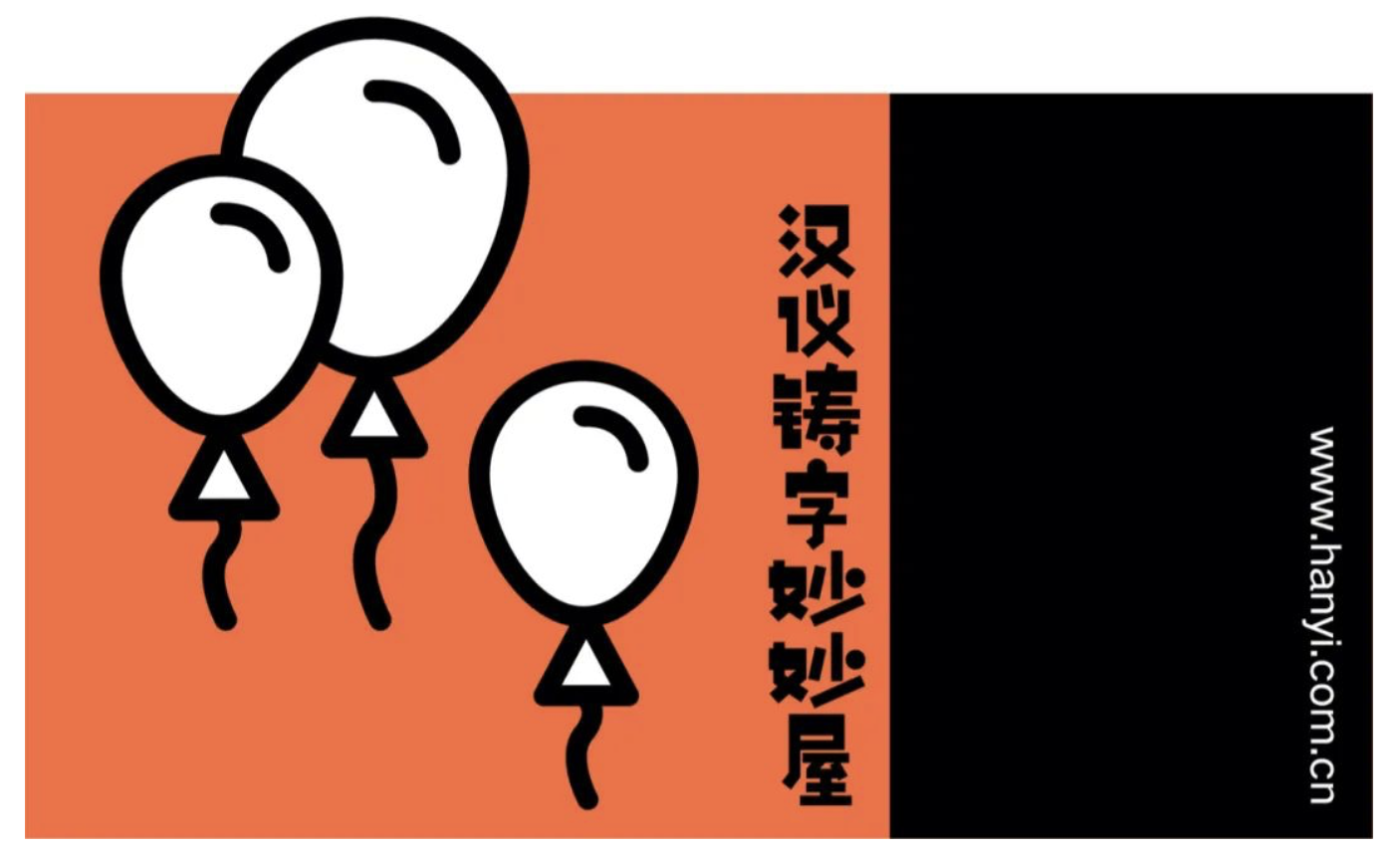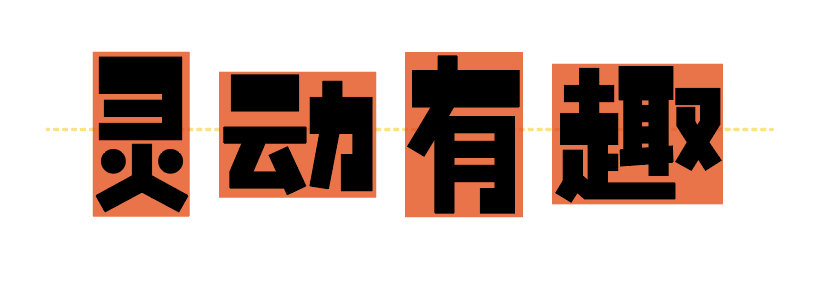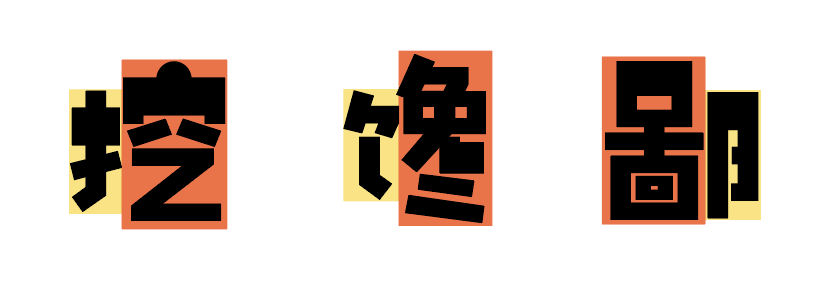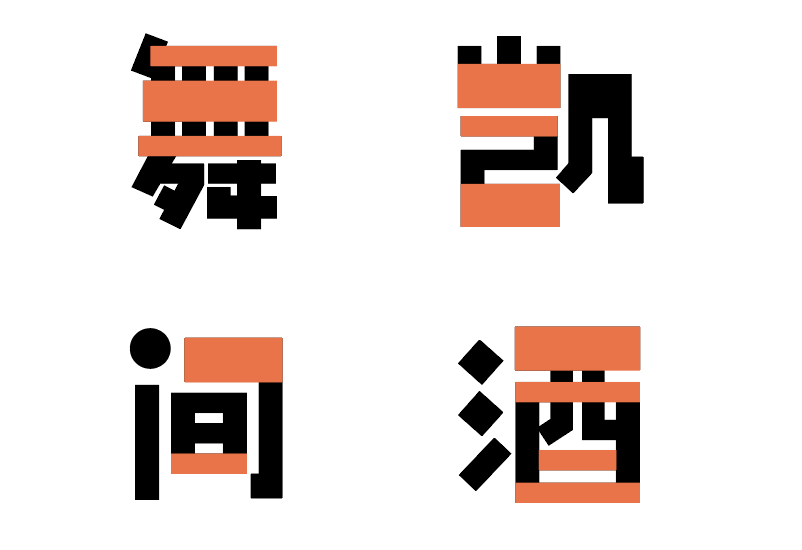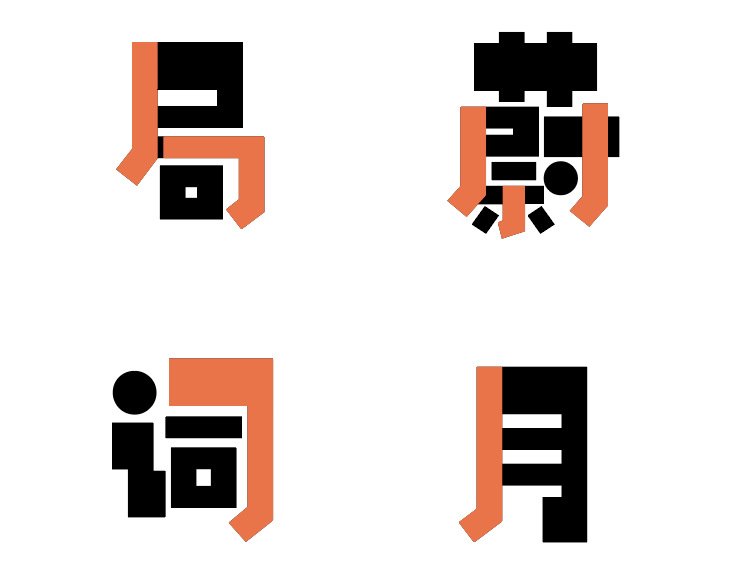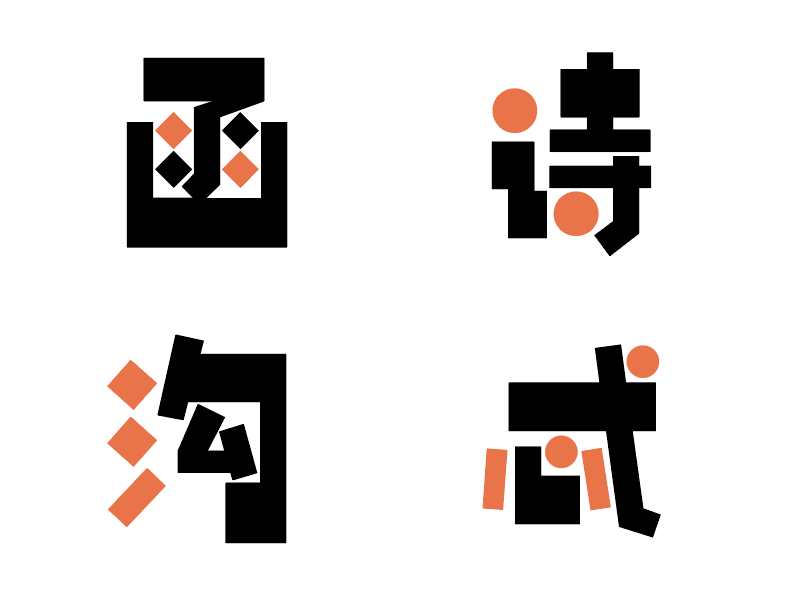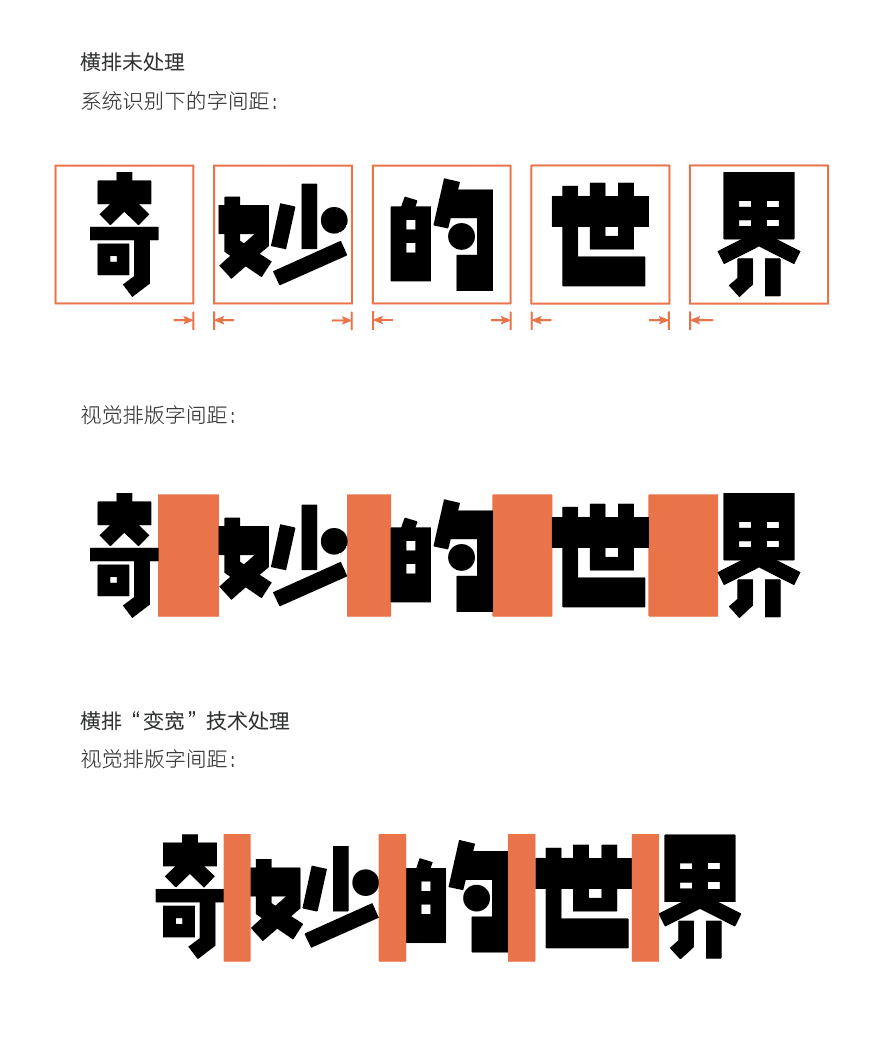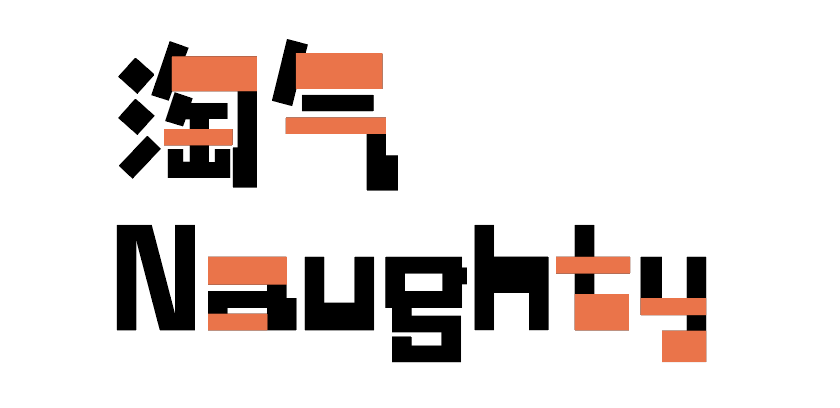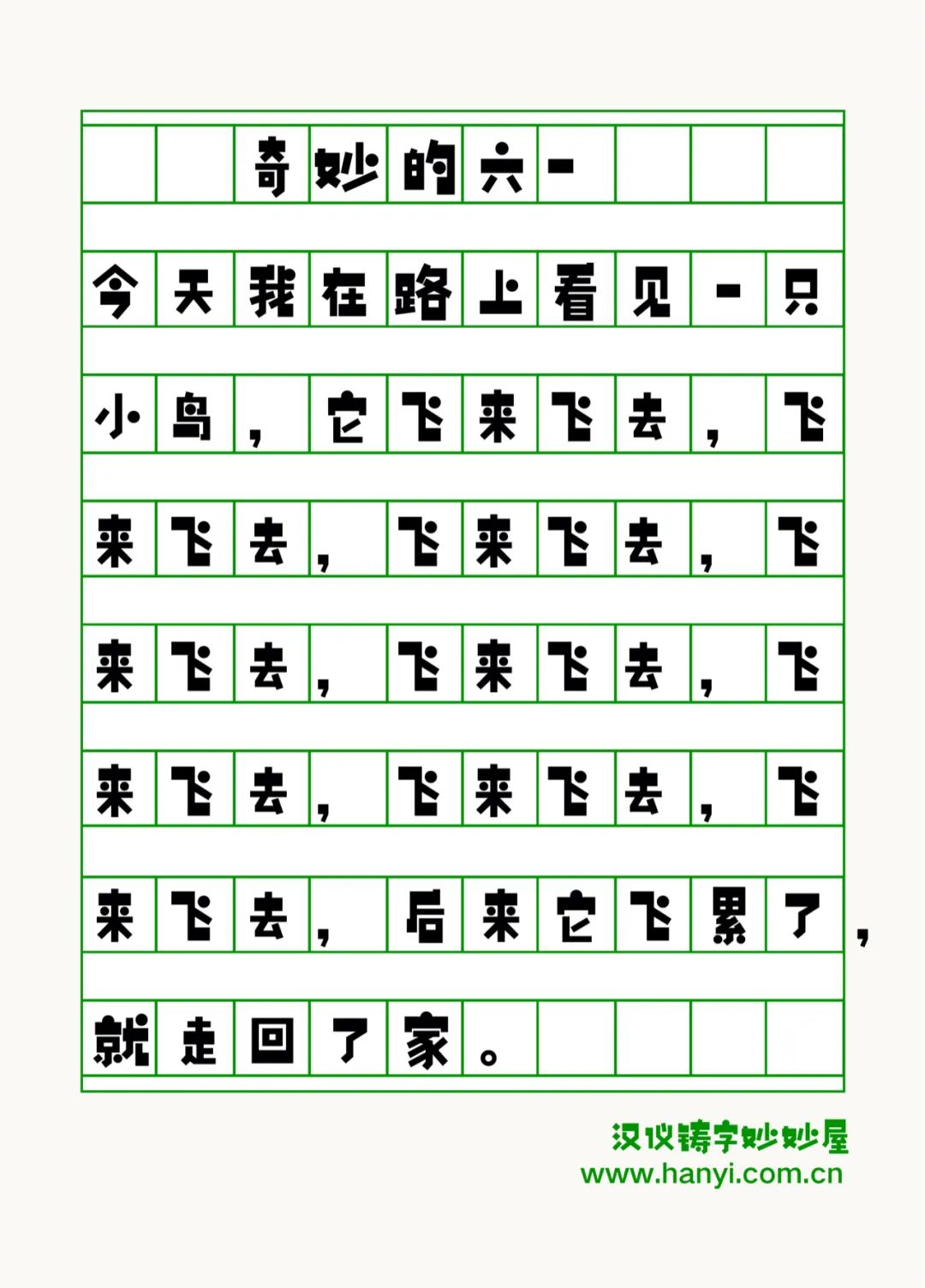
汉仪铸字妙妙屋字体介绍,汉仪铸字妙妙屋设计灵感
汉仪铸字妙妙屋 | 整体特点
“汉仪铸字妙妙屋”是汉仪旗下的“铸字社工作室”打造的一款逗趣可爱、动感活泼的创意美术标题字。它的字形变化多样,笔画粗细对比强烈,组合起来富有节奏感。
汉仪铸字妙妙屋 | 字形多变
“汉仪铸字妙妙屋”的字形多变,依据字体结构而呈现出或长或方的节奏变化,十分俏皮可爱。
汉仪铸字妙妙屋 | 结构灵活
“汉仪铸字妙妙屋”部分字体的偏旁与部首版率占比差距大,单字结构变化丰富,为字体增添了许多趣味性。
汉仪铸字妙妙屋 | 笔画活泼
“汉仪铸字妙妙屋”的横笔画粗细不一,主副笔画层次变化鲜明。在横笔画较多的字体结构当中,通过对笔画粗细及黑白空间的相对调整,使字体灰度均匀。
“汉仪铸字妙妙屋”在竖撇、竖钩和横折钩笔画的收笔处采用了折笔的处理方式,使字体更加动感活泼。
“汉仪铸字妙妙屋”点笔画的形状有圆形、矩形和菱形三种不同的设计,根据具体相关的字形而使用。
汉仪铸字妙妙屋 | 技术特点
由于“汉仪铸字妙妙屋”不同字体字面差异较大,在考虑到排版使用上的体验感后,我们在技术上采用了字间距变宽的处理方式,使字体的排版效果更加舒适自然。
汉仪铸字妙妙屋 | 中西文匹配
“汉仪铸字妙妙屋”的西文同样具有笔画粗细不一的特点,使西文更加俏皮活泼,中西文搭配使用十分和谐。
汉仪铸字妙妙屋 | 排版效果